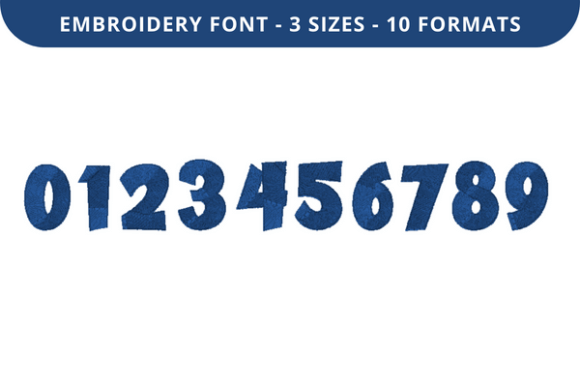
Cake Layer Font 0 to 9
Cake Layer Font 0 a 9 – Avaliação Completa
Se você busca uma fonte de bordado que una delicadeza e versatilidade, a Cake Layer Font 0 a 9 é a escolha perfeita. Desenvolvida com alta qualidade, essa fonte permite personalizar tecidos com nomes, datas ou frases especiais, trazendo um toque de elegância a cada ponto.
- Design exclusivo: números de 0 a 9 com estilo “camada de bolo”, ideal para convites, lembrancinhas e projetos de moda.
- Alta resolução: linhas nítidas e detalhes precisos que garantem um acabamento profissional em qualquer tecido.
- Versatilidade criativa: perfeito para personalizar camisetas, toalhas, almofadas, quadros de tecido e muito mais.
Por que escolher a Cake Layer Font 0 a 9?
Esta fonte de bordado foi criada para quem deseja personalizar cada detalhe de seus projetos com um toque doce e sofisticado. Seja para eventos corporativos, festas infantis ou peças de vestuário feitas sob medida, os números em camadas adicionam profundidade e charme visual que destacam seu trabalho.
A Cake Layer Font 0 a 9 é mais que uma simples fonte; é uma ferramenta de criação que eleva a qualidade e a originalidade dos seus designs de bordado. Com compatibilidade universal, alta definição e um estilo irresistível, ela se torna indispensável para quem leva a personalização a sério.